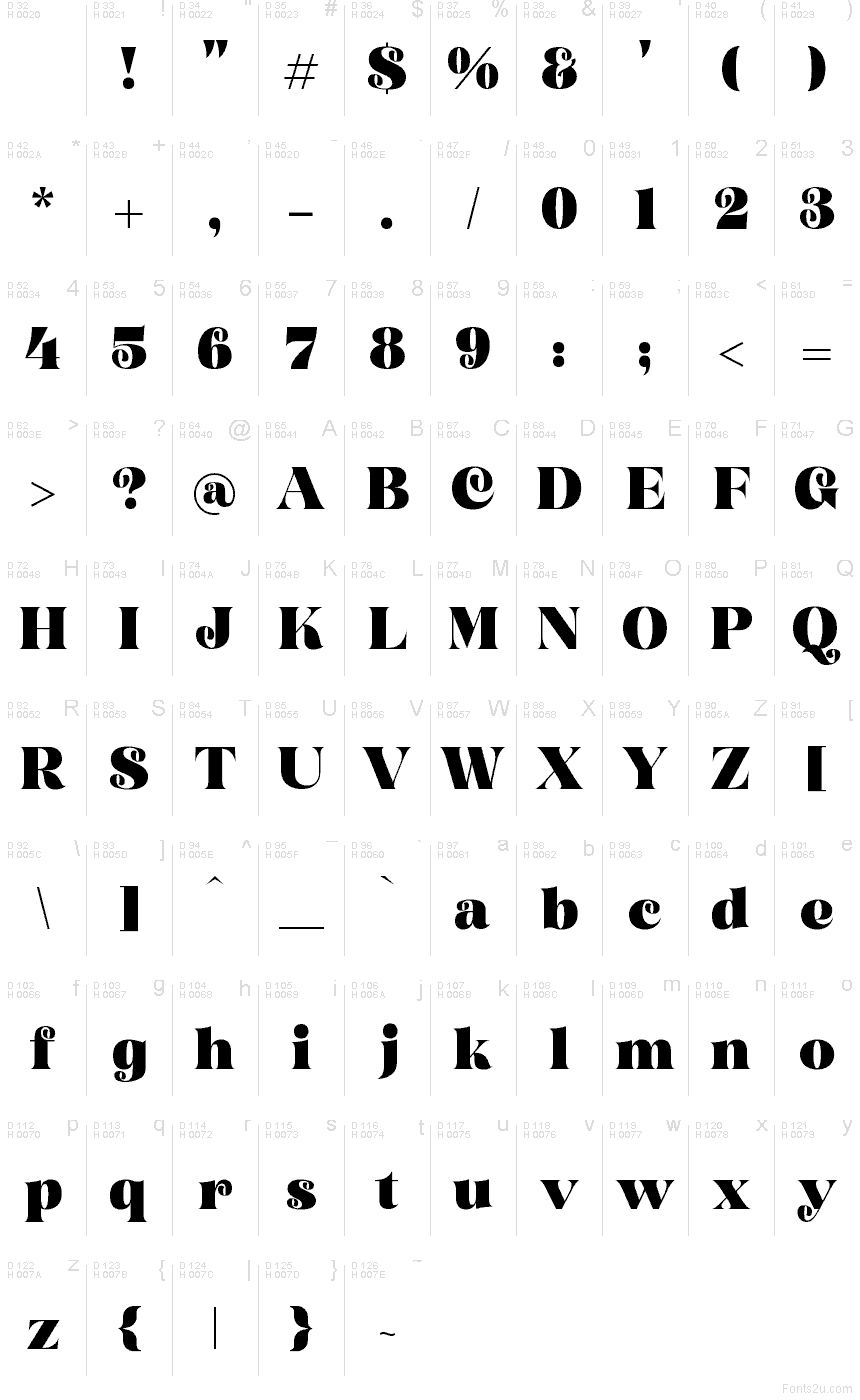
Garden Rosila od TimelessType je bezplatné, ozdobné display písmo s bohatým retro-redakčním nádechem. Písmena kombinují velké, rozmáchlé křivky s ostrými patkami o vysokém kontrastu, takže rytmus působí zároveň měkce a dramaticky – spíše jako titulky v módních časopisech než jako neutrální display písmo.
Hodí se pro branding butiků, obaly kosmetických produktů, obálky časopisů, menu kaváren a nadpisy plakátů, kde pár slov potřebuje ten správný elegantní švih. Jako bezplatné písmo skvěle funguje také pro titulní karty, citace a monogramy, protože ty smyčky dodávají krátkým textům dekorativní vzhled bez nutnosti dalších ozdob.